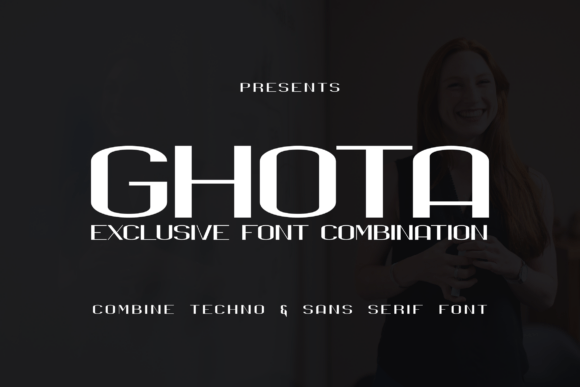
Ghota
適切なデザイン要素を見つけるのは難しい場合がありますが、Ghotaは作品を即座に引き立てる優れたコレクションを提供します。
精密に作られたGhotaは、クリーンなベクター、滑らかなタイポグラフィ、そして安心のための商用ライセンスを提供します。
POD(オンデマンド印刷)製品、結婚式の招待状、またはソーシャルメディアのグラフィックを作成している場合でも、Ghotaは理想的です。